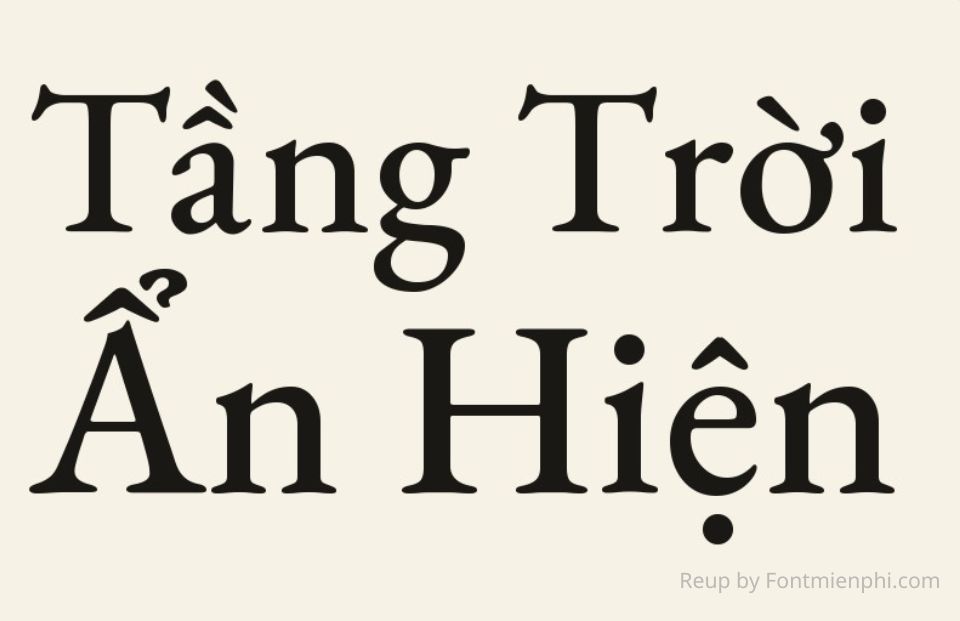
Font việt hóa EB Garamond VN
EB Garamond vốn là một font serif miễn phí trên Google Fonts và có hỗ trợ tiếng Việt ngay từ đầu. Tuy nhiên, nhận thấy bản gốc còn tồn tại một số lỗi về hiển thị dấu tiếng Việt, Font Miễn Phí đã trực tiếp tinh chỉnh và hoàn thiện lại bộ font này nhằm mang đến trải nghiệm tốt nhất cho người dùng.
Dưới đây là các chi tiết đã được Font Miễn Phí khắc phục và tối ưu:
Tinh chỉnh dấu huyền và dấu sắc kép: Dấu huyền nằm trên dấu mũ (như Tầ, Tề, Tồ) đã được dịch chuyển sang bên phải mũ. Điều này giúp dấu không còn bị chạm hoặc dính vào chữ cái đứng trước (ví dụ chữ “T” trong từ “Tầng”). Dấu sắc chồng trên mũ cũng được chúng tôi căn chỉnh lại vị trí sao cho cân đối nhất.
Điều chỉnh độ dốc: Dấu huyền và dấu sắc của các chữ thường được xoay bớt độ dốc, giúp tổng thể chiếm ít chiều cao hơn.
Tối ưu dấu mũ chữ thường (â, ê, ô): Dấu mũ được hạ thấp bớt (nhưng vẫn giữ nguyên bề rộng và độ đậm nét), đồng thời được nâng nhẹ lên để tạo ra khoảng cách thoáng đãng, dễ nhìn hơn giữa chữ cái và phần mũ.
Đồng bộ độ cao của dấu: Font Miễn Phí đã căn chỉnh để dấu mũ luôn nằm ở cùng một độ cao, bất kể có hay không có dấu thanh đi kèm (các chữ ô, ồ, ố, ổ, ỗ, ộ đều cao ngang nhau, tương tự với nhóm â và ê). Nhóm dấu trăng (ă, ằ, ắ, ẳ, ẵ, ặ) cũng được áp dụng chung nguyên tắc thống nhất này.
Cân bằng dấu ngã: Dấu ngã được xoay lại để đạt độ cân bằng hoàn hảo: hai đỉnh cao ngang nhau và hai đáy ngang nhau.
Font Miễn Phí đã áp dụng tất cả các tinh chỉnh này một cách đồng bộ cho chữ đứng lẫn chữ nghiêng, chữ thường lẫn chữ hoa, và trên toàn bộ dải độ đậm (font biến thiên 400–800).